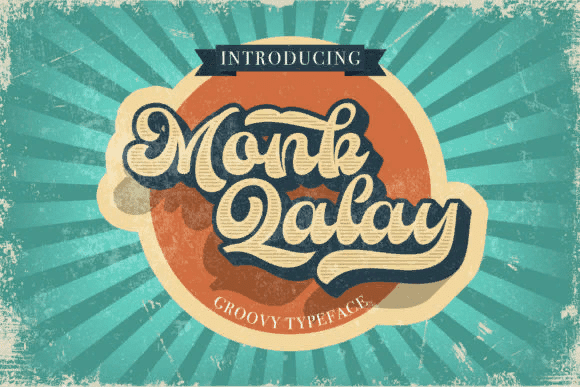
Monk Qalay - великолепный рукописный шрифт с толстыми буквами, выполненный в стиле ретро, созданный для придания стильности вашим заголовкам и логотипам.
Этот шрифт читается как сильный, уверенный и динамичный и может добавить тонны ностальгического характера в ваши проекты.